在许多产品的商品信息中会明确标注艺术字的结构,艺术字体可以用于文章的标题,也可以在装饰装帧中使用,目前主流的设计方案大多采用清晰明了简洁明快的设计主题,配以温馨的装饰,使艺术字体显得精致和华贵,那么艺术字体如何设计呢?
首先,可以将笔画进行夸张的处理,字与字之间加强种呼应关系,使其有一个穿插的效果,尽量把索要表达的感觉通过艺术字内部变化呈现出来,给大众一种想象的空间在里面,由于各个字体的基本的设计感不同,改造后的艺的艺术字体会有差异(如变得更扁平),设计变化更多,执行创建轮廓的过程不仅是压扁、提升弧度,简单粗暴压扁或者类似处理只会适得其反。
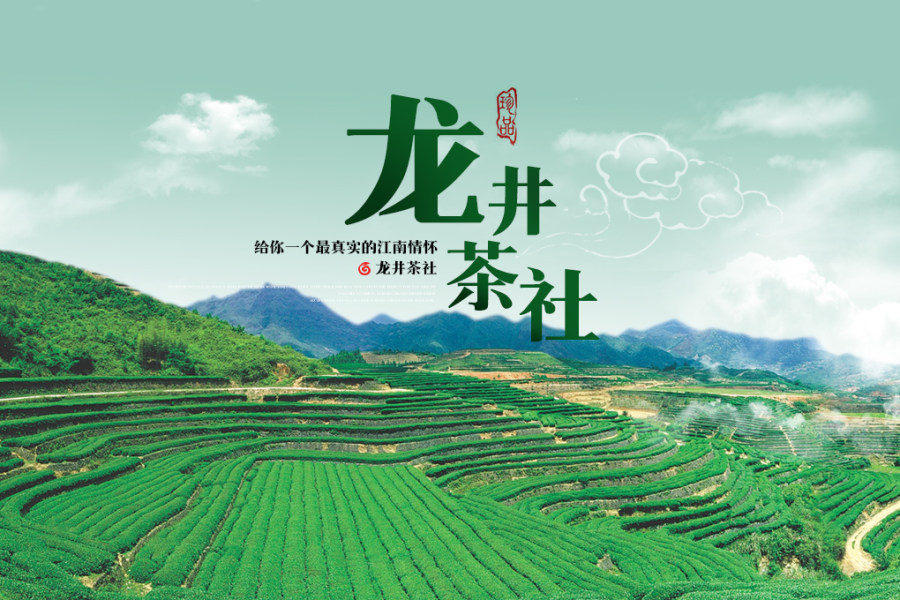
其次,可以把艺术字体笔画往下拖动,释放复合路径再拆分开,释放复合路径的时候,比如可以让里边字形的结构被填满,可重新把笔画进行归位,要充分利用路径查找器,然后把字形拖动,沿着弧度进行改变,可变成一个别的颜色,让大家看的更清晰,要避免转折点不自然,通过对笔画的挤压就可以简单实现,也可选择一种特殊的字体进行改造,亦可用这种方法去改造别的字母艺术字,呈现出完全不同的感觉。
艺术字可以是花体或者其他创意字体,同一种字体并非适用于所有的广告用字,也不能作为排版的通用字体,在设计时需追求神采俏俊,真正有灵魂的字体能够流露出设计者的天真执着,又有着浓厚的时代风采,既可以将典雅喻于其中,又可以巧拙相生,展示魅力。